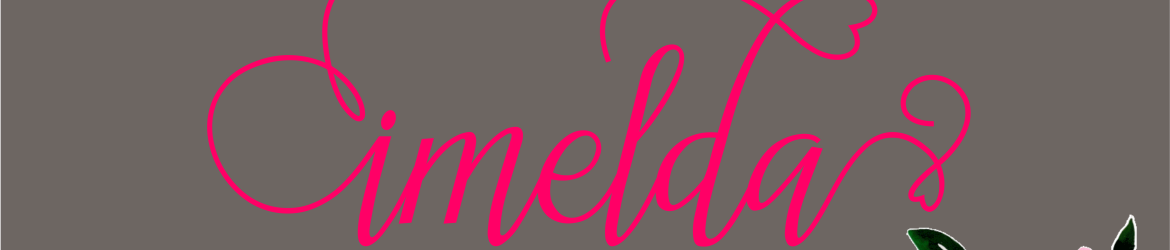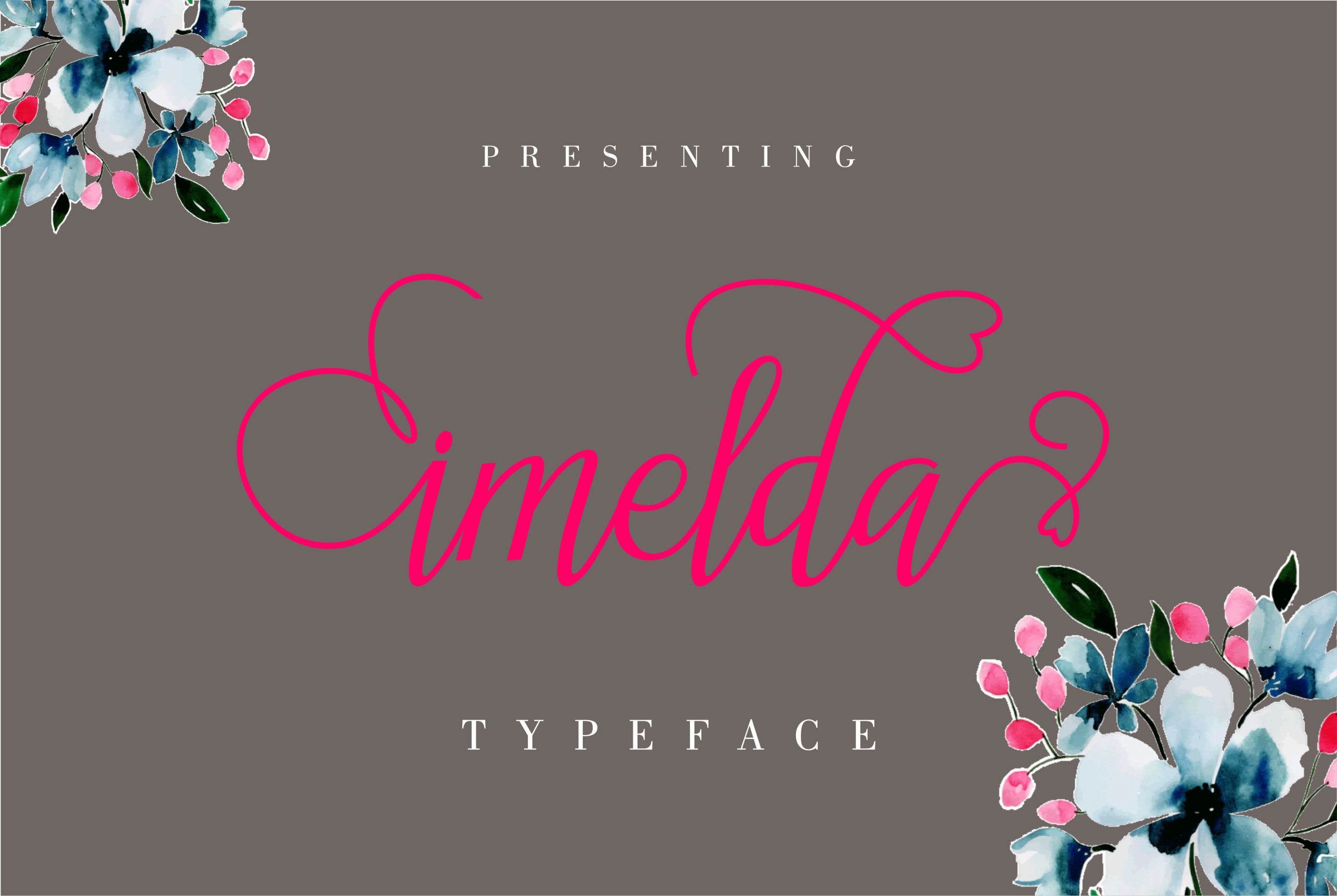
Imelda Script Font
A Imelda Script Font é uma elegante fonte escrita a mão criada pelo designer murtadha. Suavemente curvada e repleta de detalhes, esta fonte está feita para dar um toque sofisticado às suas criações digitais. Perfeita tanto para títulos quanto para textos de corpo, ela se destaca por seu charme natural e sua capacidade de criar texto com uma aparência autêntica e amigável. Para quem procura uma fonte que não apenas combina bem em projetos gráficos, mas também tem um toque pessoal, a Imelda Script é uma escolha sólida. Visite o Creative Fabrica para descobrir mais sobre outras maravilhas da fontes e design.